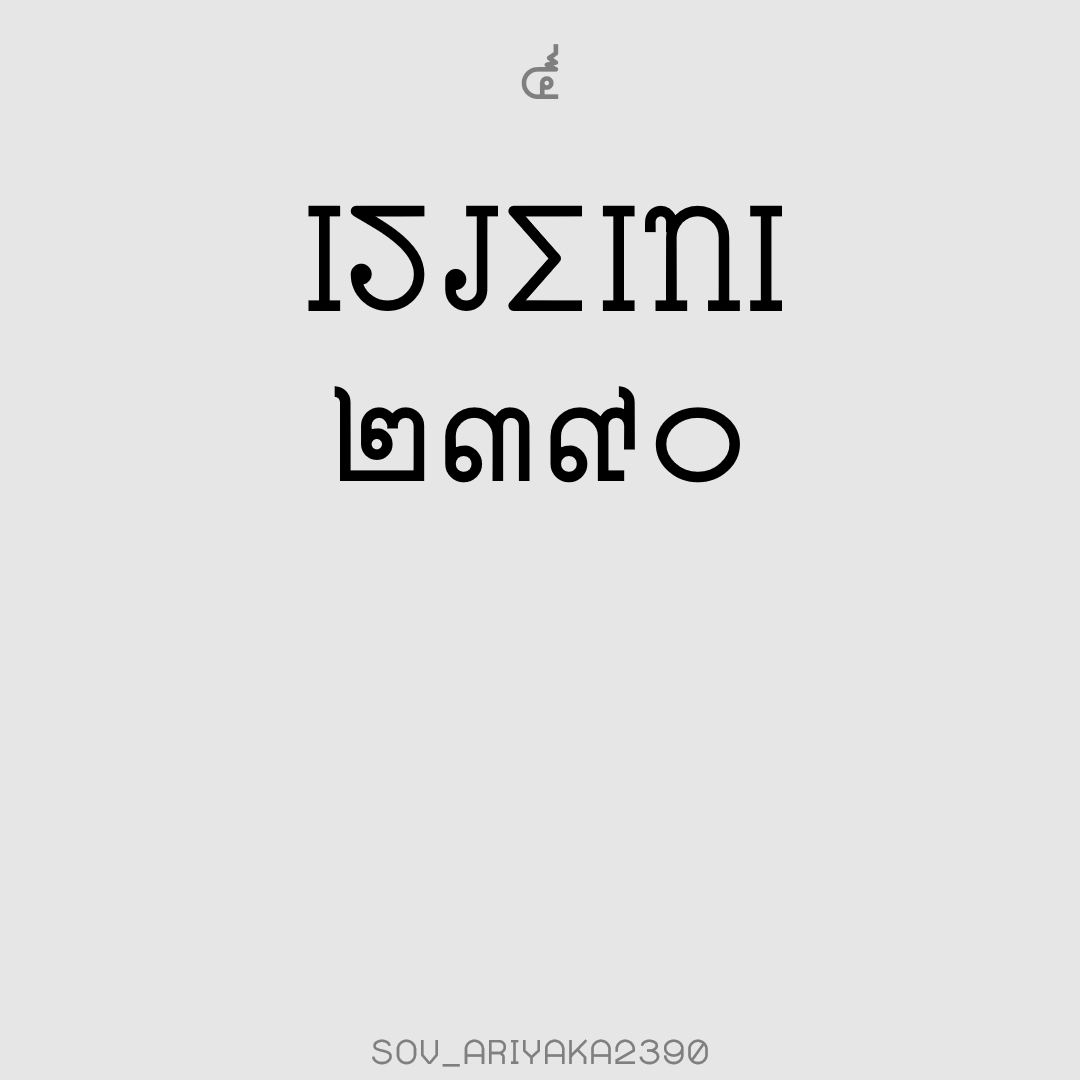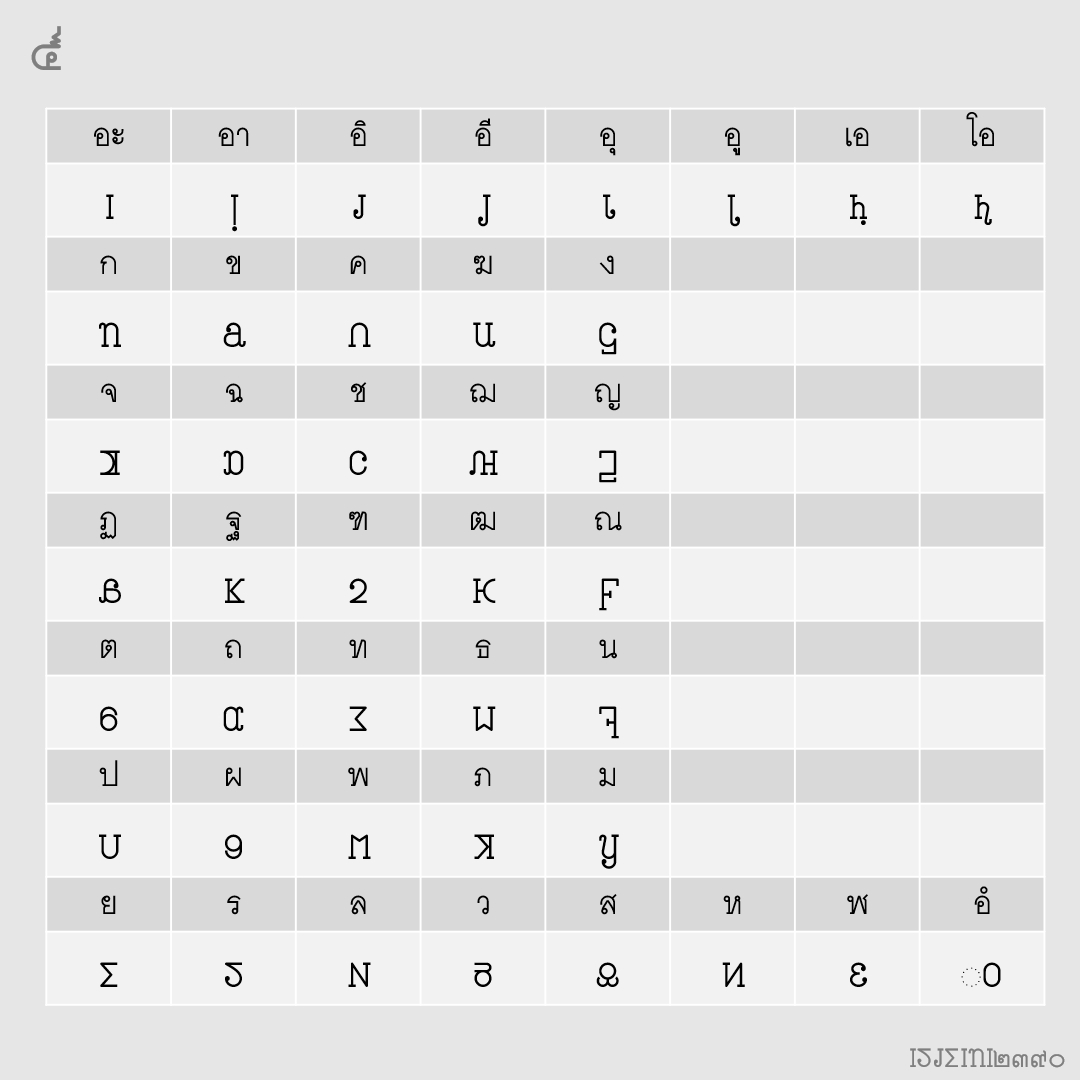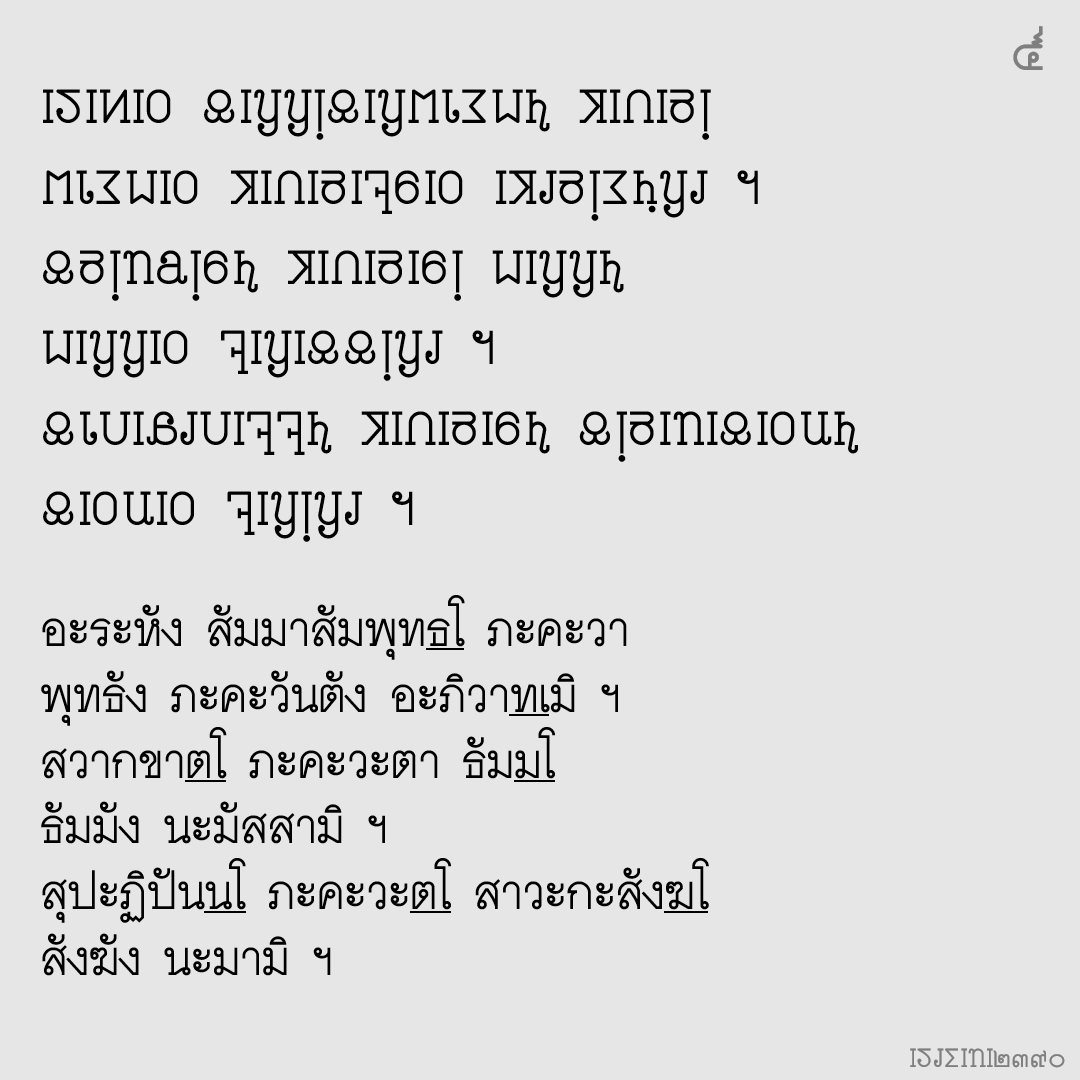
ฟอนต์ อริยกะ๒๓๙๐
ทดลองทำฟอนต์อริยกะ ตัวพิมพ์ สำหรับภาษาบาลีเท่านั้น ..วิธีพิมพ์เหมือนพิมพ์ตัวสะกด แต่สระจะต้องตามหลังพยัญชนะเสมอ (ไม่มีสระหน้า เช่น เ โ ก็ต้องพิมพ์ตามพยัญชนะ) ฟอนต์ตัวปรกติ มีเฉลยใต้บรรทัด ถ้าชำนาญแล้ว ใช้ฟอนต์ตัวหนา
ปล. แถม ฟอนต์อริยกะพินทุ สำหรับคนเคยพิมพ์อักษรไทยพินทุอยู่แล้ว เอาไปเปลี่ยนฟอนต์ได้เลย ไม่ต้องพิมพ์ใหม่
ชื่อฟอนต์ : อริยกะ๒๓๙๐
ทดลองทำฟอนต์อริยกะ ตัวพิมพ์ สำหรับภาษาบาลีเท่านั้น ..วิธีพิมพ์เหมือนพิมพ์ตัวสะกด แต่สระจะต้องตามหลังพยัญชนะเสมอ (ไม่มีสระหน้า เช่น เ โ ก็ต้องพิมพ์ตามพยัญชนะ) ฟอนต์ตัวปรกติ มีเฉลยใต้บรรทัด ถ้าชำนาญแล้ว ใช้ฟอนต์ตัวหนา
ปล. แถม ฟอนต์อริยกะพินทุ สำหรับคนเคยพิมพ์อักษรไทยพินทุอยู่แล้ว เอาไปเปลี่ยนฟอนต์ได้เลย ไม่ต้องพิมพ์ใหม่
ข้อมูลอักษรอริยกะจาก ตำนานวัดบวรฯ
น่าจะใช้ยาก ไม่เป็นที่นิยม